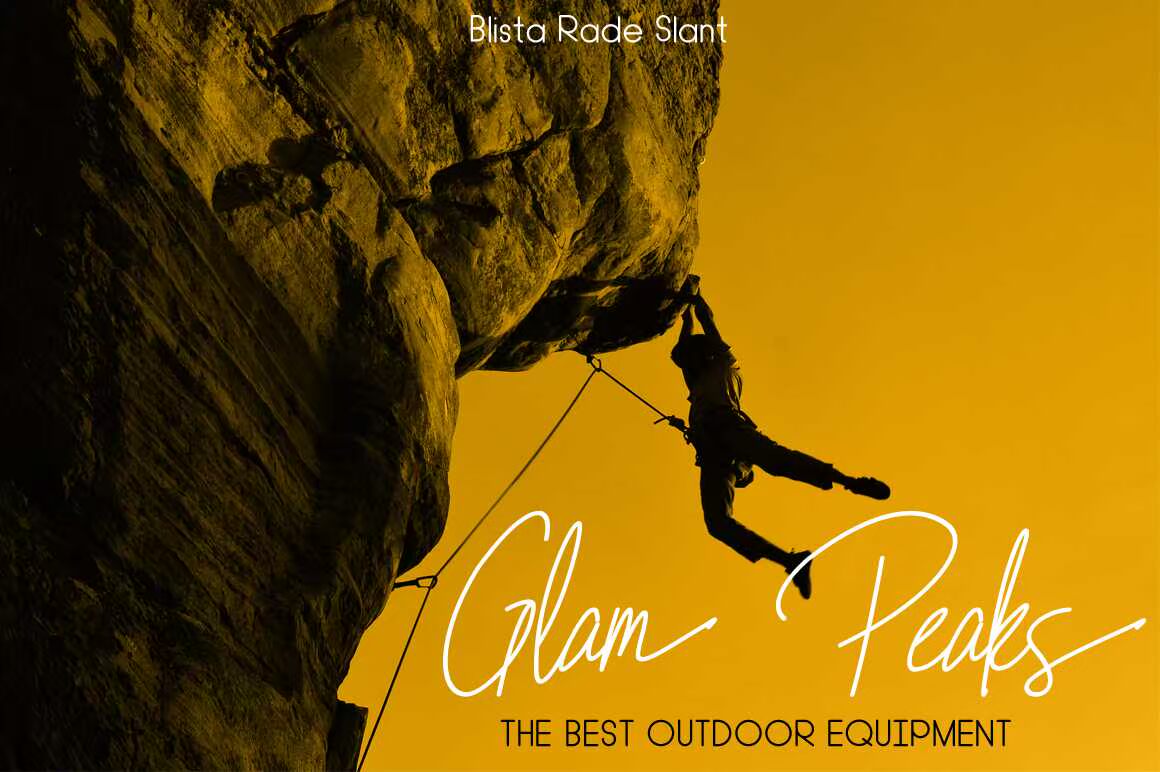
Blistarade是一款与Anatural和Clean Flow OneLine相关的手写签名。Blistarade采用倾斜版本,使此字体适合于任何项目。例如,马克摄影、任何类型的签名样式徽标、个人品牌、名片、,t-Shirt Standmore…Blistarade是一款手工签名,描述了与Anatural和Clean Flow OneLine的联系。Blistarade采用斜版,使这款字体适用于任何项目。例如,马克摄影、任何类型的签名样式徽标、个人品牌、名片、t-Shirt Standmore…